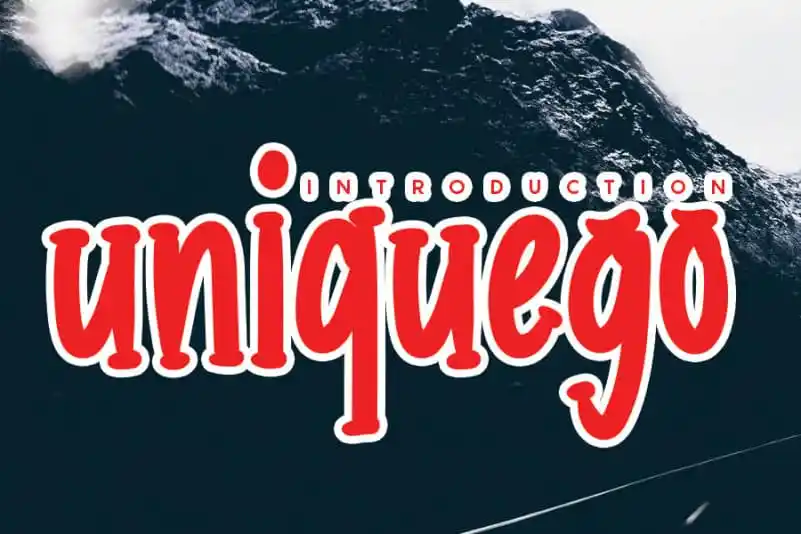
uniquego Display Font – Download Grátis
A “uniquego Display Font” é uma escolha perfeita para aqueles que buscam uma tipografia alegre e descontraída, sem deixar de lado a funcionalidade robusta. Ela traz um ar de simplicidade junto com um toque leve de originalidade, garantindo uma combinação equilibrada entre clareza e personalidade. Esta fonte é perfeita para qualquer projeto onde você deseja destacar sua identidade visual de maneira criativa — seja em logomarcas, projetos de marca, redes sociais ou até mesmo DIY. Com “uniquego Display Font”, você pode explorar suas ideias de forma única e divertida. Seja uma nova ferramenta para seu arsenal gráfico ou a fonte perfeita para aquele projeto personalizado que está em sua mente, ela tem tudo o que você precisa para fazer algo realçado e original.